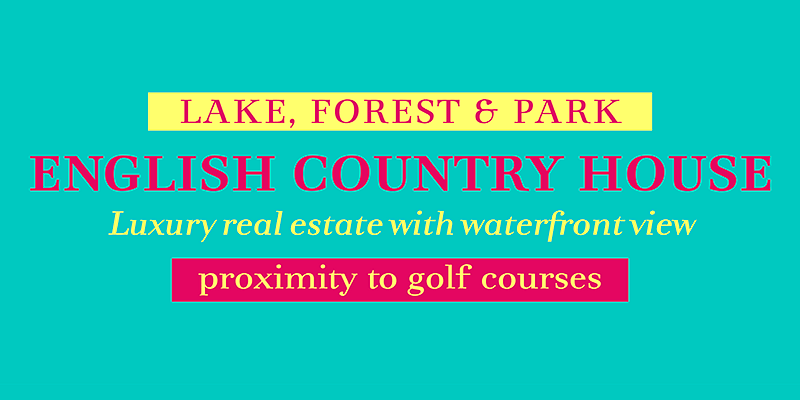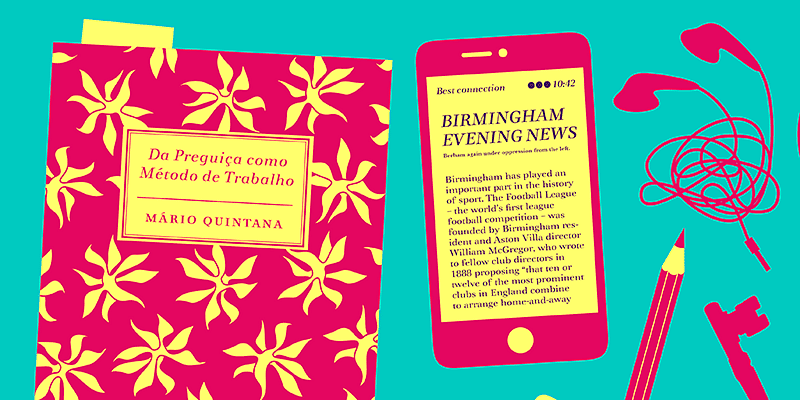
Dedica es un tipo de letra inusual con serifas asimétricas pronunciadas. Ideal para cabeceras y titulares, el encanto y la elegancia del diseño pueden darle vida a cualquier mensaje.